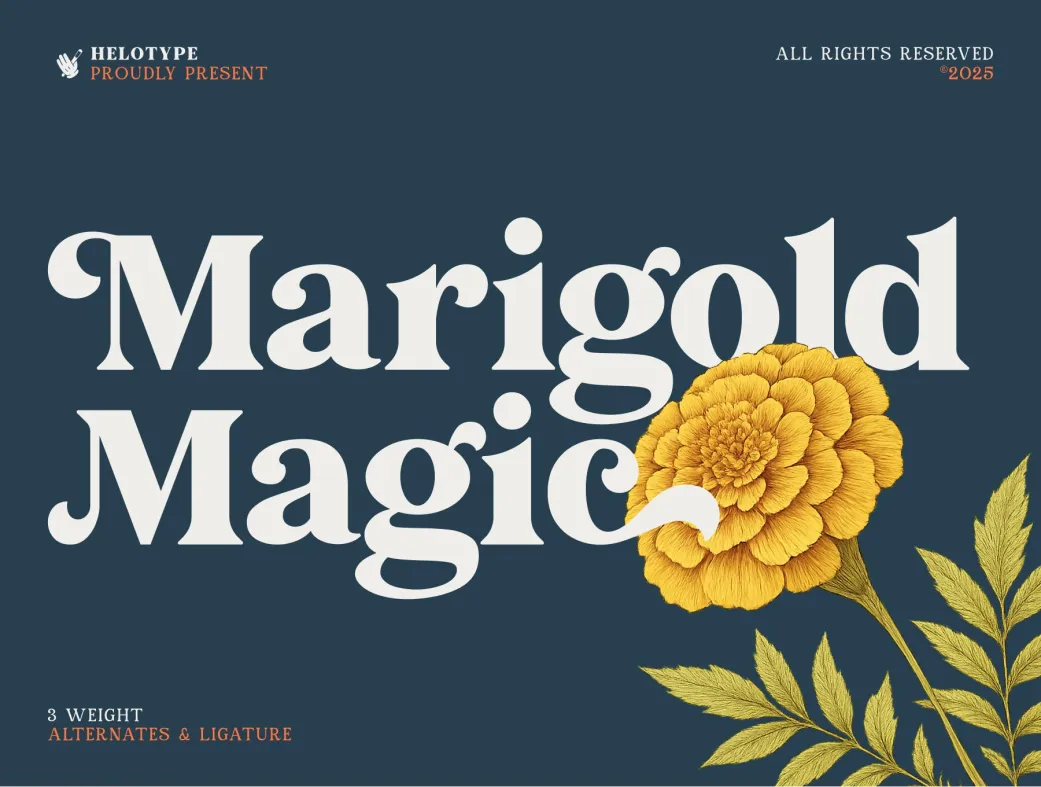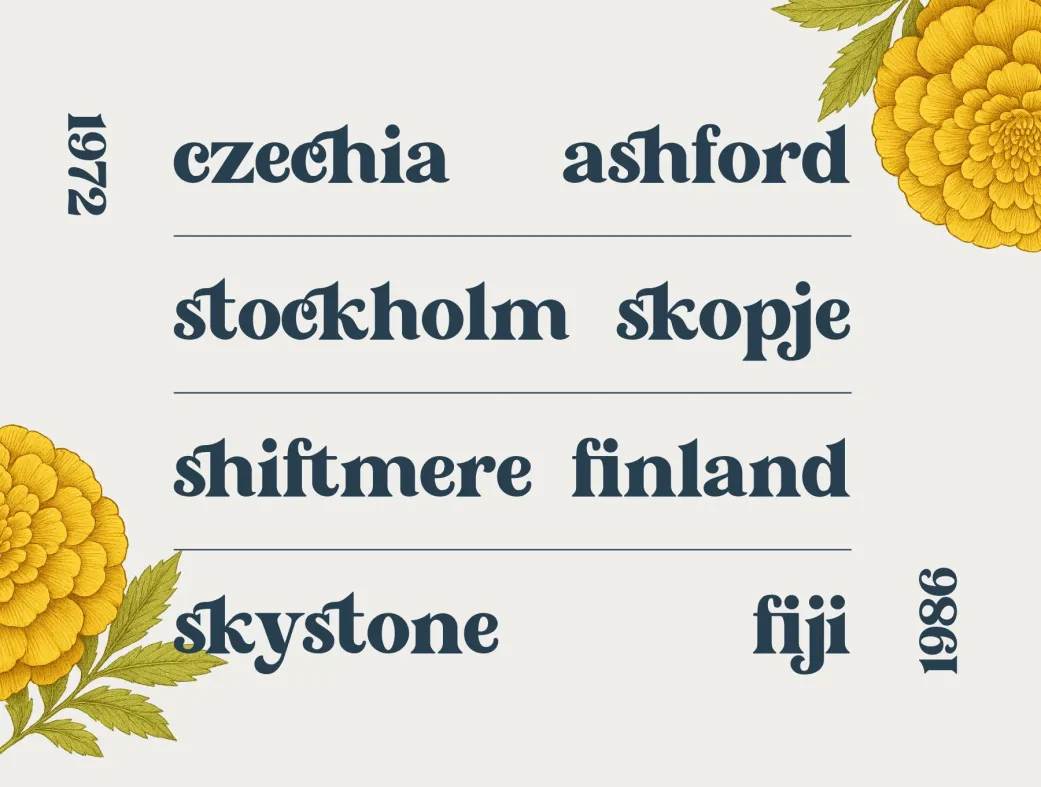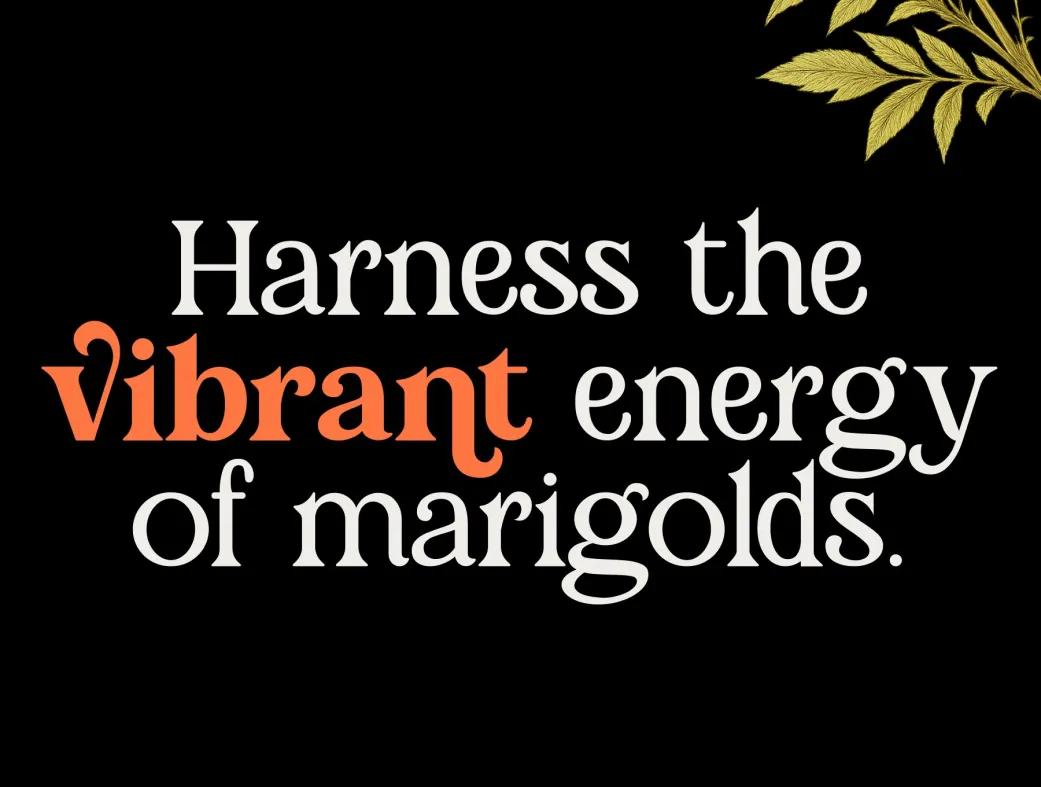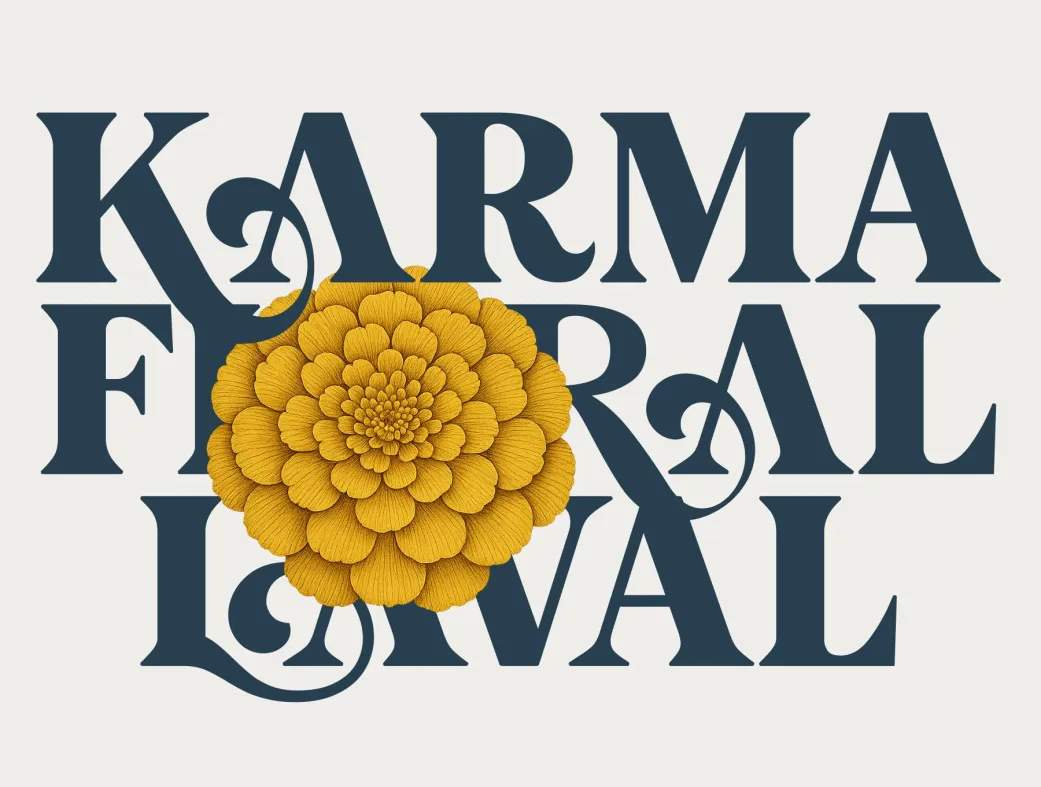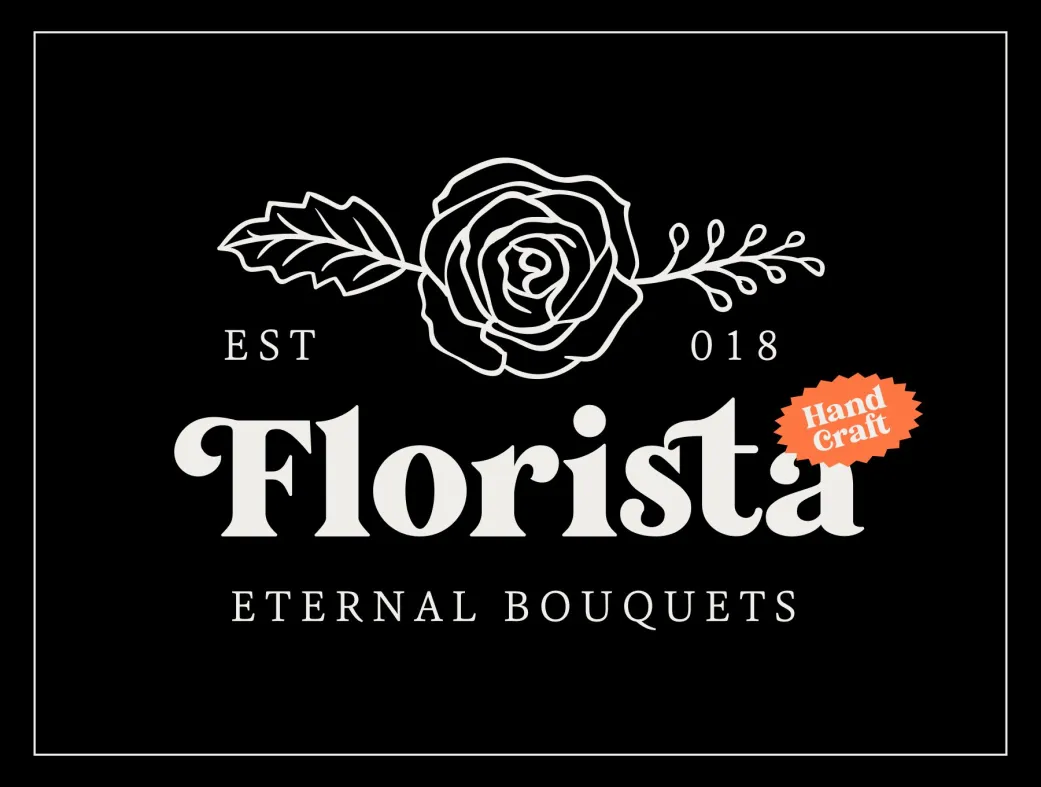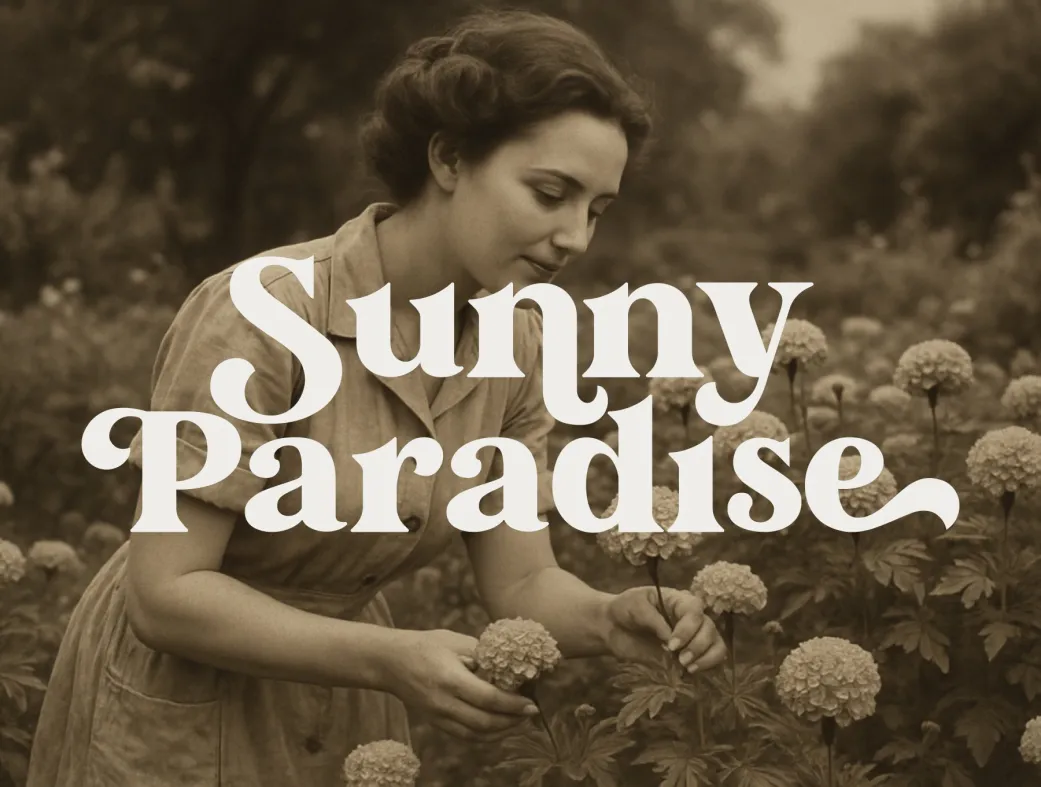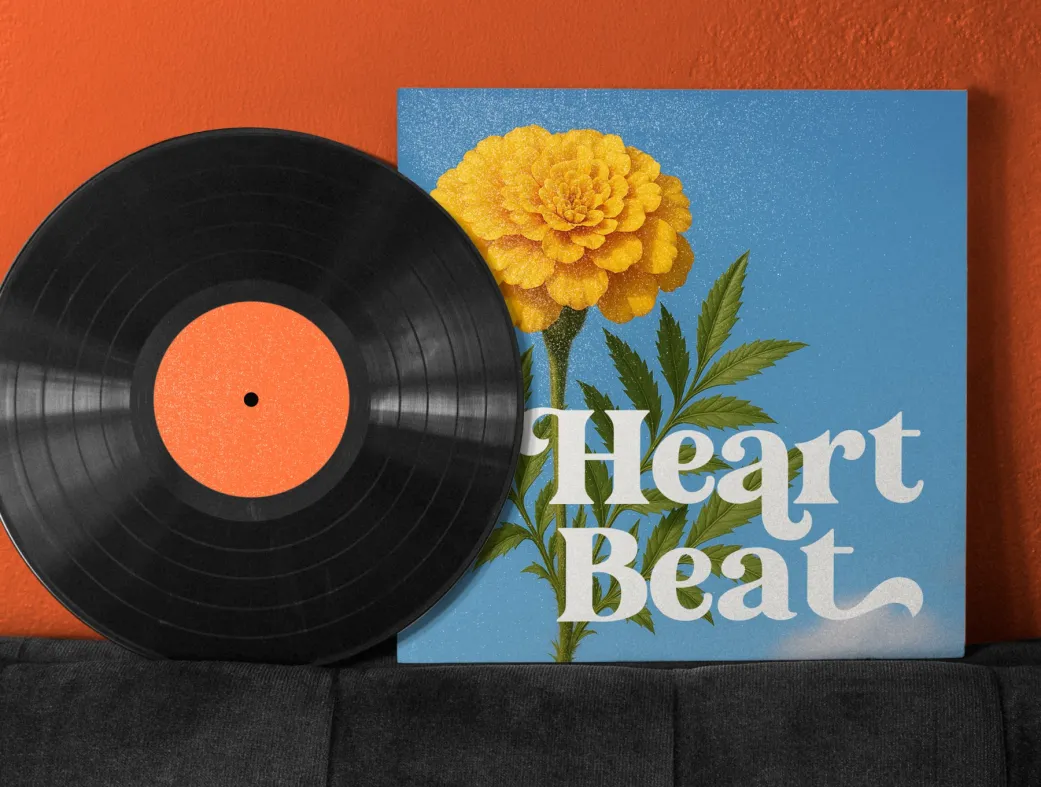
فونت سریف قدیمی ماریگلد مِجیک | Marigold Magic
فونت سریف قدیمی ماریگلد مِجیک، انتخابی مناسب برای طرح‌های شیک و کلاسیک!
Marigold Magic - Vintage Serif Font
فونت سریف قدیمی ماریگلد مِجیک | Marigold Magic | MarigoldMagic
فونت سریف قدیمی ماریگلد مِجیک (Marigold Magic) یک فونت الهام‌گرفته از دوران گذشته است که با جذابیت و ظرافت خود، بهترین انتخاب برای طراحان گرافیک است. این فونت با سه وزن مختلف، جایگزین‌ها، پشتیبانی از چند زبان و لیگاتورها، گزینه‌ای بی‌نظیر برای افزودن لمسی از کلاسیک بودن به طرح‌های شماست.
فونت ماریگلد مِجیک با طراحی منحصر به فرد خود، به راحتی می‌تواند در پروژه‌های مختلف گنجانده شود. با سه وزن مختلف (سبک، متوسط و سنگین)، این فونت به شما امکان می‌دهد تا در طراحی‌های خود تنوع ایجاد کنید. وجود جایگزین‌ها و لیگاتورها این فونت را به یک ابزار قدرتمند برای ایجاد طراحی‌های خلاقانه تبدیل کرده است. به علاوه، پشتیبانی از چند زبان، این امکان را برای طراحان فراهم می‌آورد که به راحتی از این فونت در پروژه‌های بین‌المللی خود استفاده کنند.
فونت ماریگلد مِجیک برای طراحان حرفه‌ای و مبتدیان مناسب است. این فونت می‌تواند برای طراحی دعوتنامه‌های عروسی، پوسترهای با تم vintage و لوگوهای شیک استفاده شود. برای بهترین نتیجه، توصیه می‌شود از این فونت در ترکیب با رنگ‌های ملایم و زمینه‌های ساده استفاده کنید تا زیبایی و جذابیت آن به خوبی نمایان شود.